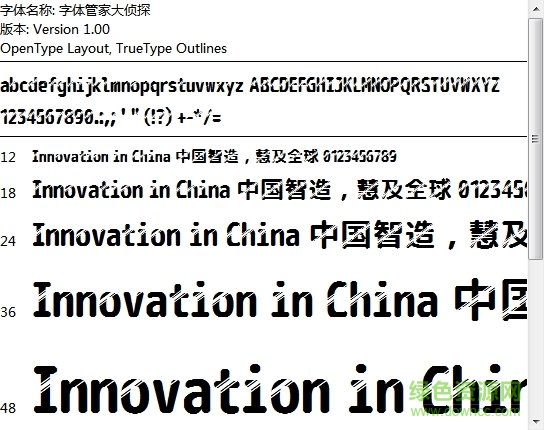
大偵探字體是字體管家推出的一款中文字體,文字結(jié)構(gòu)嚴(yán)謹(jǐn)大方,傾斜虛化的設(shè)計(jì)讓你的藝術(shù)設(shè)計(jì)更加出色,快來(lái)綠色資源網(wǎng)試試吧!
當(dāng)排除了所有其它的可能性,還剩下一個(gè)時(shí),不管有多么的不可能,那便是真相。沒(méi)錯(cuò),這就是大偵探存在的力量,字體大氣而神秘,給人一種震懾感。
Aa大偵探,也叫作字體管家大偵探字體,美術(shù)字體設(shè)計(jì)風(fēng)格,斜體白色的設(shè)計(jì)給文字帶來(lái)更為舒適明亮的視覺(jué)體驗(yàn),可以廣泛運(yùn)用在平面設(shè)計(jì)、包裝設(shè)計(jì)、海報(bào)設(shè)計(jì)等場(chǎng)合!